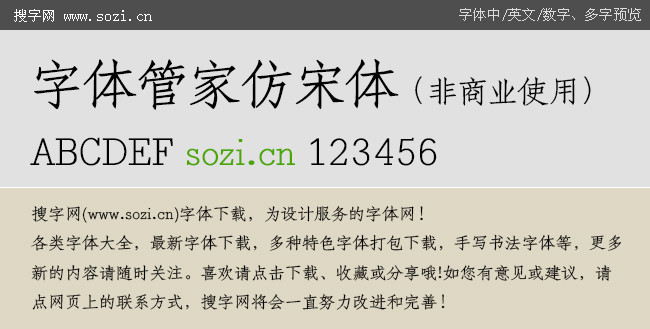
字體管家仿宋體(非商業(yè)使用)
搜字網(wǎng)給大家提供一款字體管家仿宋體(非商業(yè)使用)中文字體下載,字體管家仿宋體(非商業(yè)使用)是一款字形清秀的中文字體,該字體結構優(yōu)美,識別性好,適合海報設計、包裝畫冊等宣傳廣告等應用(此字體為個人非商用版,商用可以聯(lián)系QQ:1006760504)。